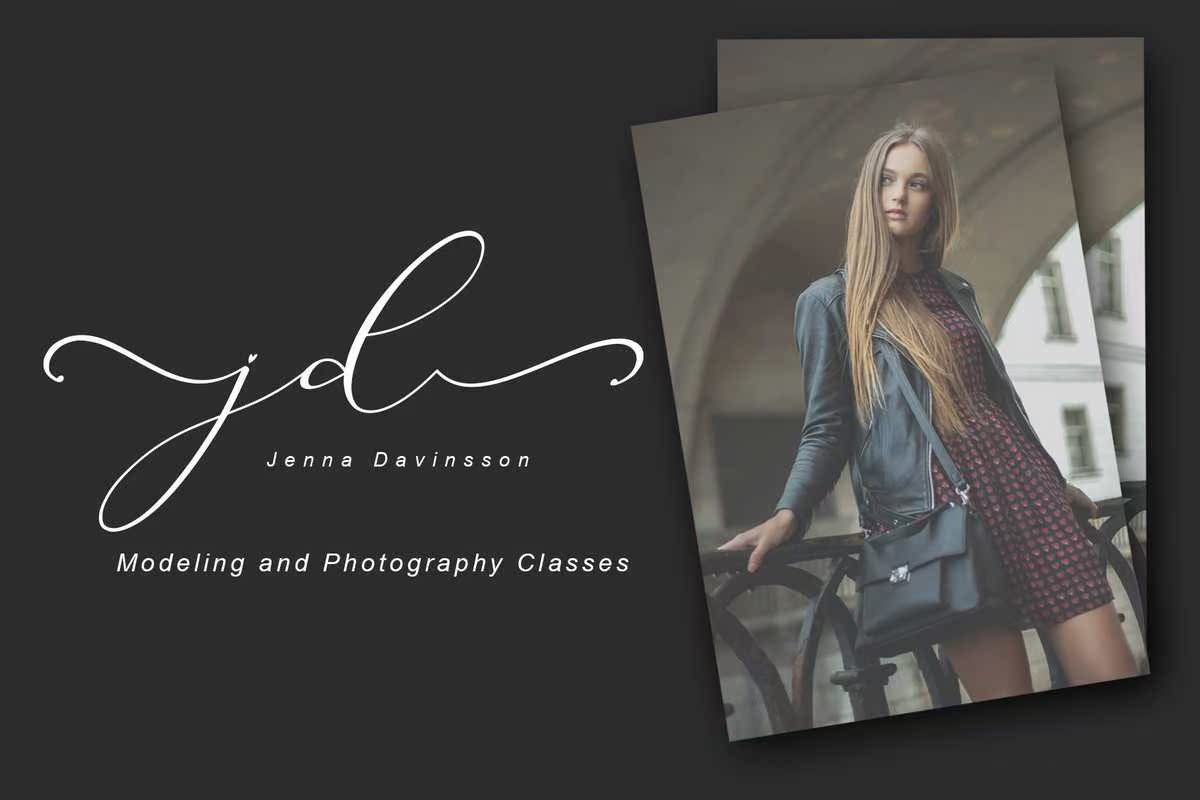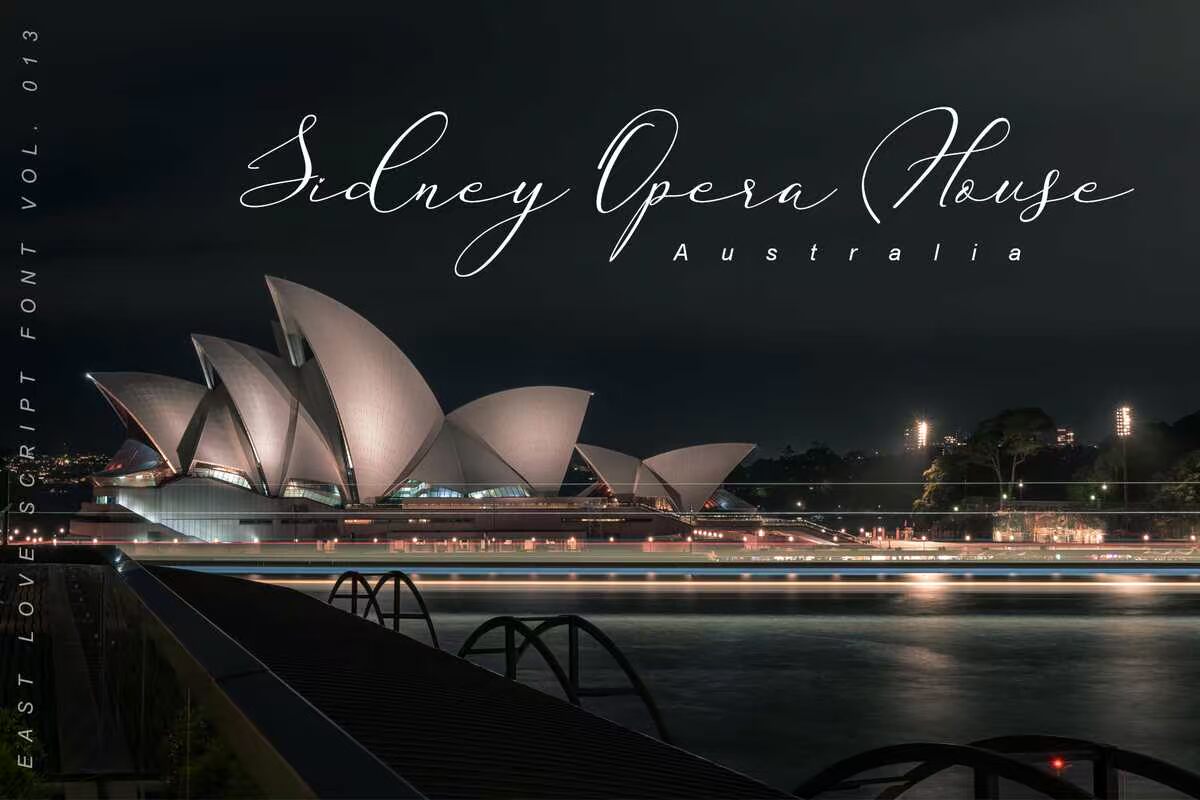
EastLove是一个具有松散主题的奇特脚本字体。它具有美丽且平衡的特征,因此,它与广泛的设计池相匹配。将此Chunkylettered字体添加到您的设计中,并注意它如何使其充满活力!这个字体是经过编码的,意味着你可以访问所有的符号和SWASHEASE!EastLove是一个具有松散主题的奇特脚本字体。它具有美丽且平衡的特征,因此,它与广泛的设计池相匹配。将此Chunkylettered字体添加到您的设计中,并注意它如何使其充满活力!这个字体是经过编码的,意味着你可以访问所有的符号和SWASHEASE!